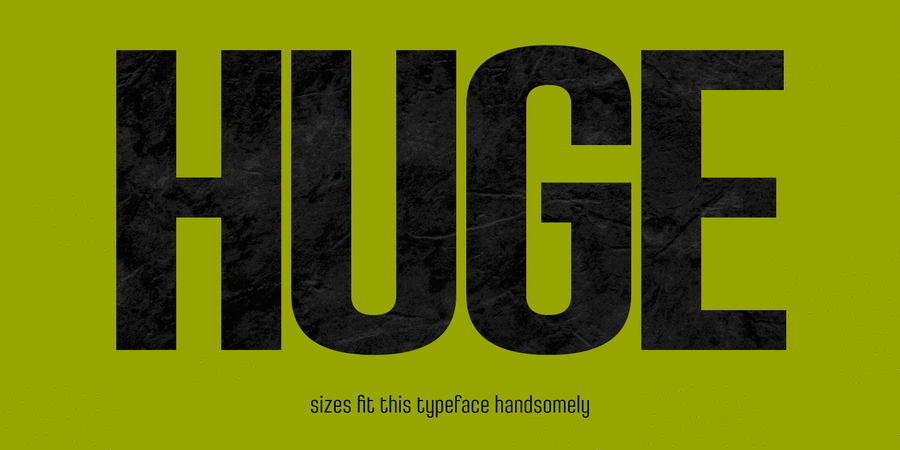
Densa (8 шрифтів)
Опис гарнітури DensaЦе вузький гротеск з трохи нетрадиційними закінченнями. Його компактний дизайн робить його дуже ефективним для економії місця, а альтернативні форми літер роблять його дуже цікавим варіантом для акциденції, наприклад, логотипів, пакування, плакатів. Шрифт був задуманий для заголовків і коротких текстових блоків. Densa складається з 8 накреслень. Кожне містить капітель та символи для багатьох мов на латинці й кирилиці. Шрифт розробив Пабло Балселлс у 2020 році.
Асоціації з сімейством шрифтів DensaОсобистість і характер гарнітури:
делікатний, чистий, легкий, прохолодний, свіжий, модний, стрункий, невагомий, прозорий, тонкий, глобалізований, глобалістічний, інтимний, дротяний, рівний, худий, статичний, високий, серйозний, дорослий, міський, ритмічний, діловий, стабільний, стійкий, Простий, солідний, гучний, важливий, переконливий, прямокутний, твердий, надійний, впевнений, сильний, індустріальний, техногенний, мотивуючий, амбітний, відповідальний, крутий, інженерний, креслярський, спортивний, стиснений, помітний, монументальний, вузький, чіткий, робочий, строковий, монотонний, важкий, авторитетний, невідкладний, наполегливий, напористий, яскравий, активний
парфумерія, лосьйон, краса, туалетна вода, шампунь, косметика, дизайн, гігієна, чистота, кінотеатр, Місто, бізнес, хмарочос, новини, політика, промисловість, техніка, верстат, інструмент, прилад, електростанція, енергетика, завод, тренажери, наука, технології, інженер, рок-н-рол, спорт, будматеріали, будівництво, машинобудування, сировина, нафта, газ, нерухомість, архітектура, торгівля, магазин, робочий, селфі, вантажівка, далекобійник, мафія, цегла, казино, прапор, цигарки Гарнітура асоціюється з віком: